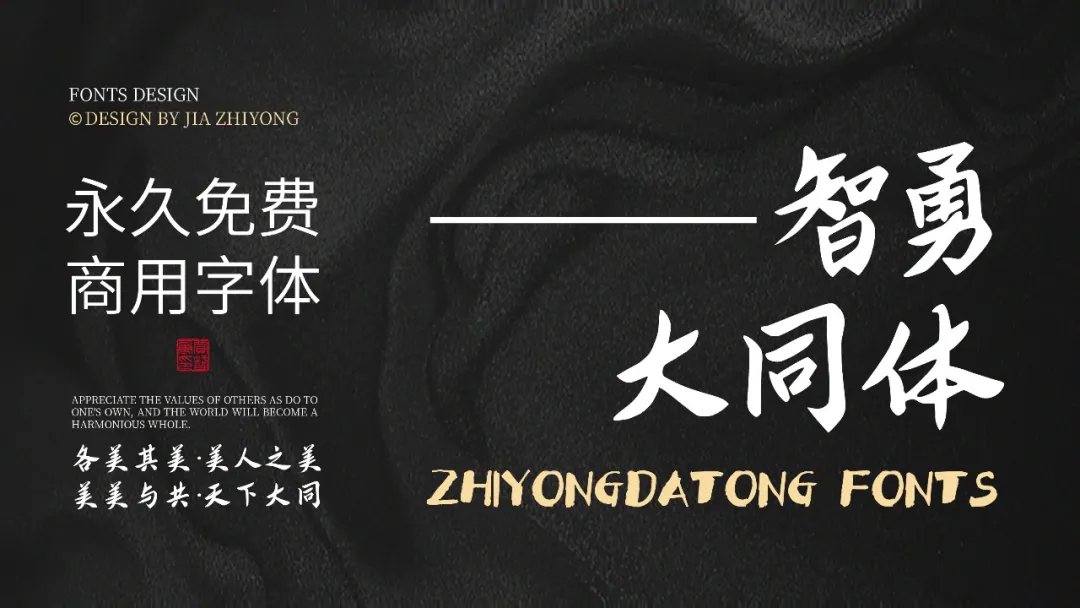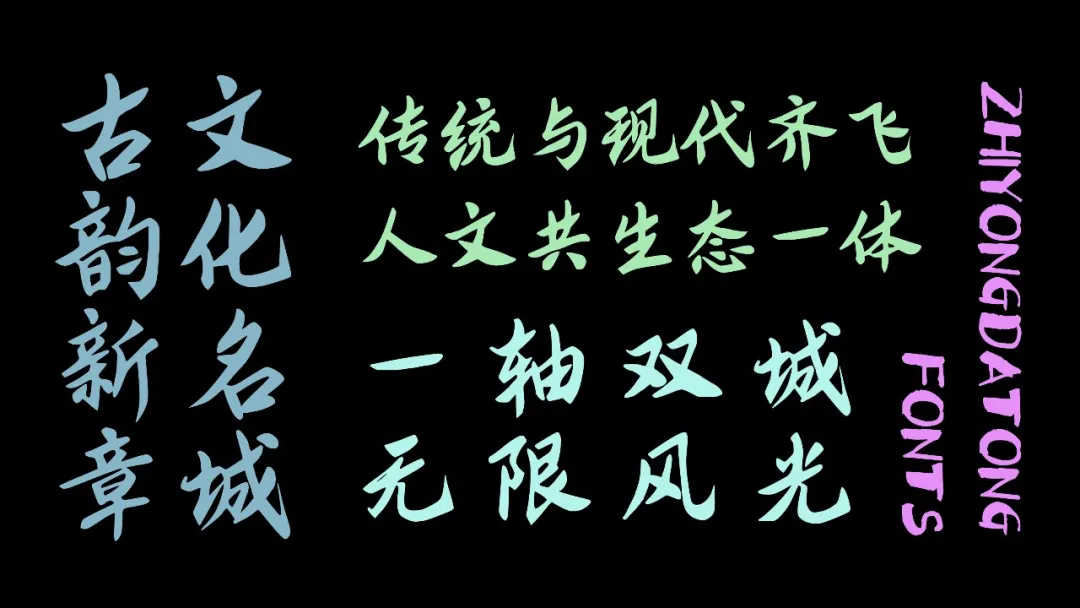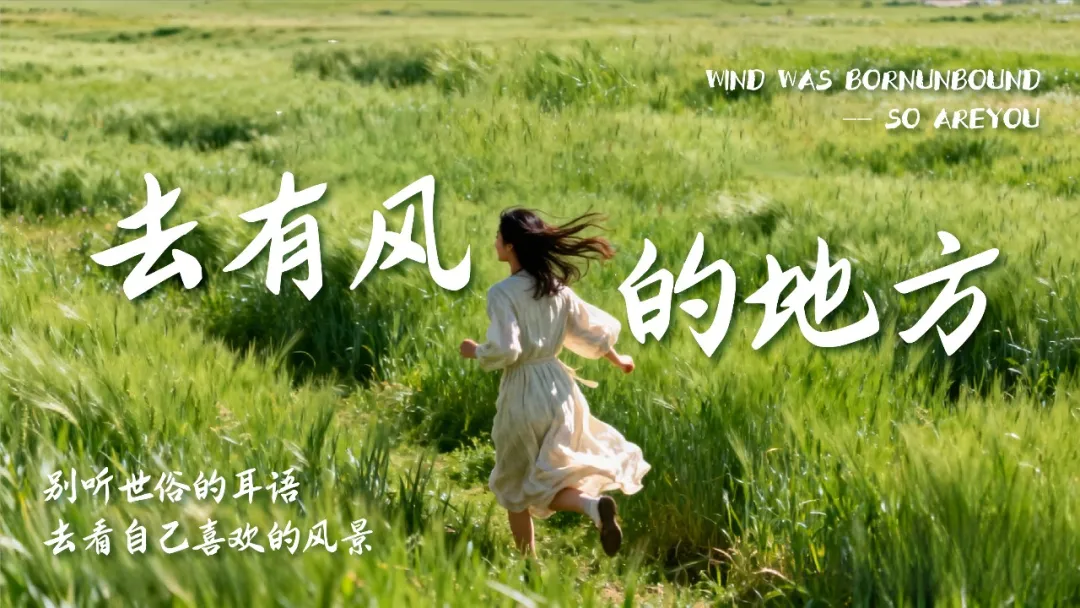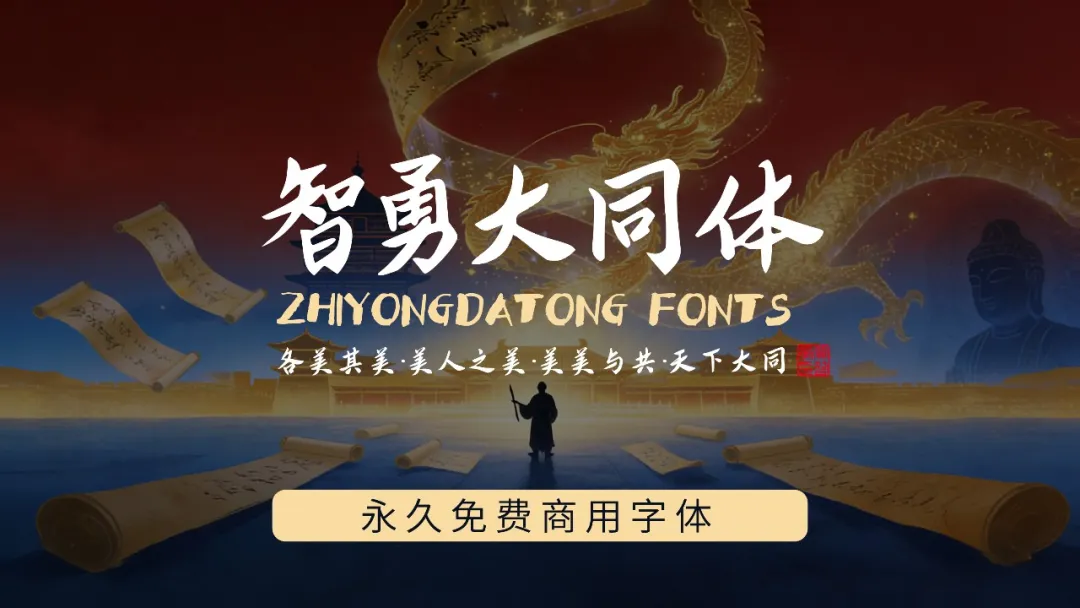
智勇大同体由设计师贾智勇历时两年多打造的一款手写字体。作者先是通过毛笔手写,再借助AI辅助扩展为完整字库,最后再逐字进行打磨调整,最终完成了这款包含 6763 个常用汉字的中文字体。
“智勇”:取自设计师本人的名字“贾智勇”,象征字体的起点与人格投射;
“大同” :一方面指设计师的家乡山西大同,这座拥有北魏、辽金等辉煌历史的文化古城为其提供了丰富的设计灵感;另一方面也指“天下大同”的哲学思想,即“各美其美,美人之美,美美与共,天下大同”。